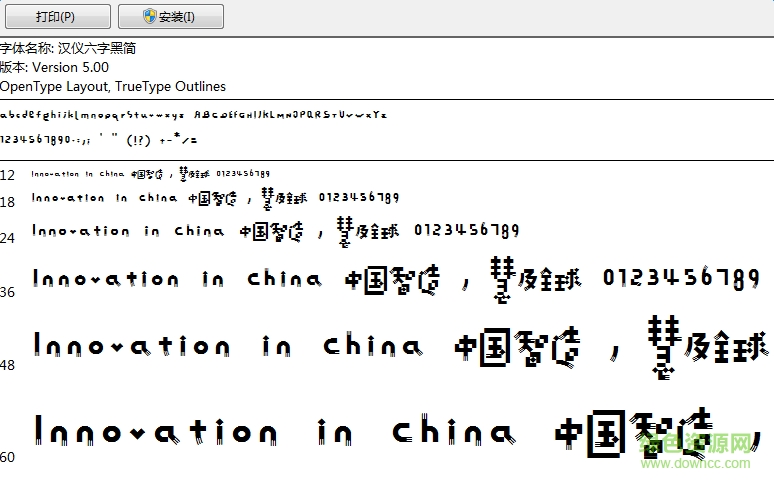
軟件介紹 軟件標(biāo)簽: 漢儀字體 字體 漢儀六字黑簡是漢儀字體庫中的一款個性字體,該字體可以廣泛應(yīng)用于廣告設(shè)計、宣傳海報、ppt、影視制作以及任何使用文字的領(lǐng)域,有需要的朋友可以免費(fèi)下載收藏。字體安裝方法方法一:控制面板/字體/文件/安裝新字體;方法二:直接將字體復(fù)制到C:\WINDOWS\Fonts。方法三:針對win7系統(tǒng),用戶只需選中字體右鍵安裝即可。注意事項本站所有字體資源僅供個人學(xué)習(xí)與參考,如需商業(yè)使用請到相關(guān)官網(wǎng)授權(quán)。 本字體如果商用,請聯(lián)系漢儀字體官方獲得授權(quán)。 軟件截圖 上一張下一張(1 / 1) 安裝詳細(xì)截圖 猜你喜歡 漢儀字體 漢儀字體 漢儀字體有哪些?漢儀字體下載大全收錄了所有好看的、經(jīng)典的漢儀字體合集,漢儀字體是由北京漢儀科印信息技術(shù)有限公司創(chuàng)作,這些字體種類齊全,各具特色、應(yīng)用領(lǐng)域廣泛,喜歡漢儀字體的朋友歡迎來綠色資源網(wǎng)免費(fèi)下載使用! 查看更多>> 阿里巴巴普惠字體 26.00M/中文/0.8/官方ttf版下載 漢儀天宇風(fēng)行體 21.41M/中文/5.0/下載 漢儀蘇澤立行楷精修版簡 3.01M/中文/4.0/免費(fèi)版下載 漢儀正圓(共7款) 17.96M/中文/2.8/ttf免費(fèi)版下載 漢儀可愛字體打包 41.20M/中文/5.0/14款下載 漢儀曉波花月圓字體 1.89M/中文/0.0/下載 其他版本下載 標(biāo)題 大小 更新日期 下載 下載地址 電腦版 漢儀六字黑簡 點擊報錯 軟件無法下載或下載后無法使用,請點擊報錯,謝謝! 關(guān)閉報錯反饋 請描述您所遇到的錯誤,我們將盡快予以修正,謝謝! *必填項,請輸入內(nèi)容 本類最新 漢儀孟瑞體ttf v1.0 官方版 漢儀字庫免費(fèi) 132款 阿里巴巴普惠字體 官方ttf版 漢儀字體打包大全 for Mac 蘋果電腦版_ 共131款字體 漢儀純愛情書拼音體 ttf版 漢儀北魏寫經(jīng)w字體 免費(fèi)版 相關(guān)文章 Photoshop字體安裝使用方法和技巧 如何解決“無法新增字體”問題 Win 7系統(tǒng)安裝字體方法 網(wǎng)頁字體大小設(shè)置方法 怎么改網(wǎng)頁字體大小 在Linux系統(tǒng)中安裝字體的幾種方法 windows7字體顯示問題:打開某些程序的時候顯示的是亂碼 用戶評論 熱門評論 最新評論 發(fā)表評論 查看所有評論(0) 昵稱: 請不要評論無意義或臟話,我們所有評論會有人工審核. 字?jǐn)?shù): 0/500 (您的評論需要經(jīng)過審核才能顯示)